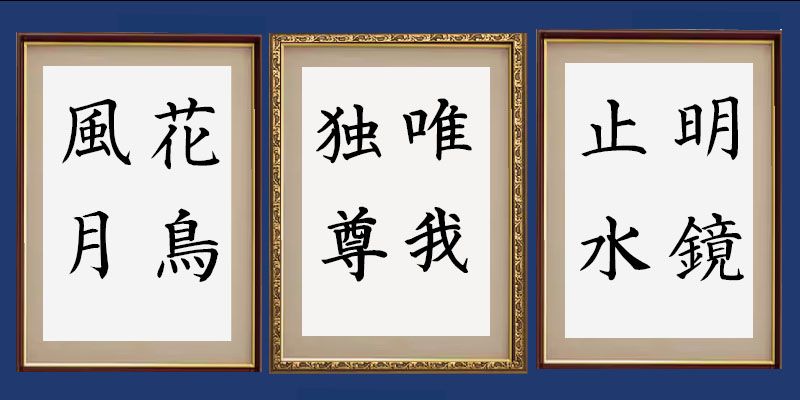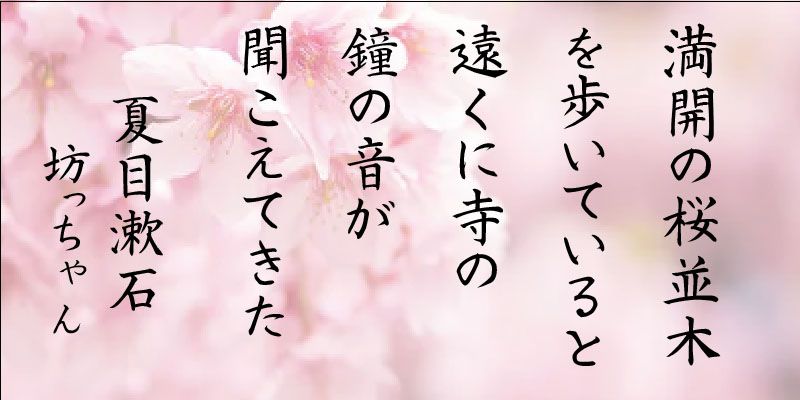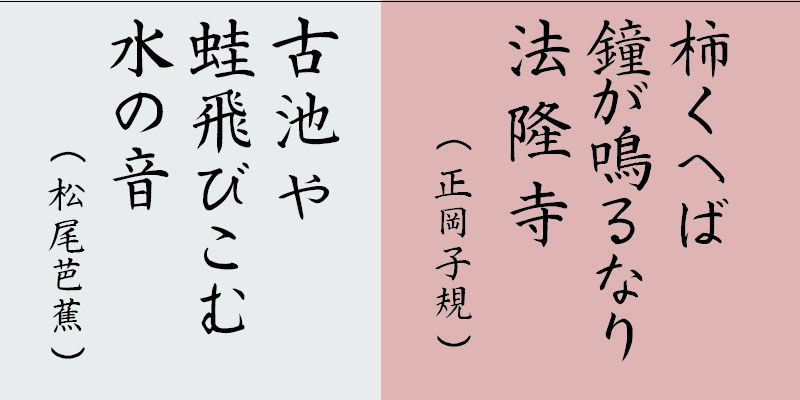
Diese Pinselschrift verleiht Direkt-Mail (Postwurfsendungen) und ähnlichen Kommunikationsmitteln eine freundliche, persönliche und menschliche Anmutung.
Jede Schrift dieser Schriftfamilie enthält alphanumerische Zeichen, Hiragana- und Katakana-Zeichen, die als proportionale Glyphen gestaltet sind und jeweils eine eigene Zeichenbreite aufweisen.
Mit über 60 Jahren Erfahrung in der Kalligraphie hat der Kalligraph Hakushu Nakamoto Pinselschriften mit schönen und kunstvoll handgeschriebenen Buchstabenformen geschaffen. Er arbeitet als professioneller Kalligraph und bietet maßgeschneiderte Dienstleistungen an, um unterschiedlichste Kundenanforderungen zu erfüllen. Durch die Verwendung von Nakamotos Designs werden Sie immer mehr mit der Kunst der traditionellen Kalligraphie vertraut.